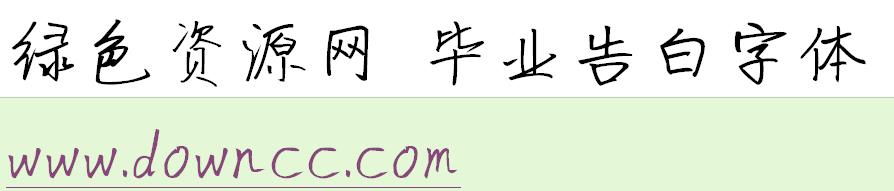
畢業(yè)告白字體ttf這款字體在情書體中十分受歡迎,每一個(gè)字體都擁有濃厚的情書告白意味,十分不錯(cuò),在用戶使用的時(shí)候能夠讓你感受到情書告白般的樂趣,在與小伙伴們之間進(jìn)行交流的時(shí)候使用這款字體將更加不錯(cuò)!
這款字體是小編搜集的情書體中比較不錯(cuò)的字體了,正如每一個(gè)人都有一個(gè)想要在畢業(yè)時(shí)告白的女神一樣,這款字體將帶給你不錯(cuò)的告白悸動(dòng)。
這款字體在使用的時(shí)候?qū)⒛軌蚝芎玫倪_(dá)到用戶所需的字體顯示效果
在眾多的情書體中這款字體將占據(jù)不錯(cuò)的地位,擁有十分精美的行文結(jié)構(gòu),精美異常